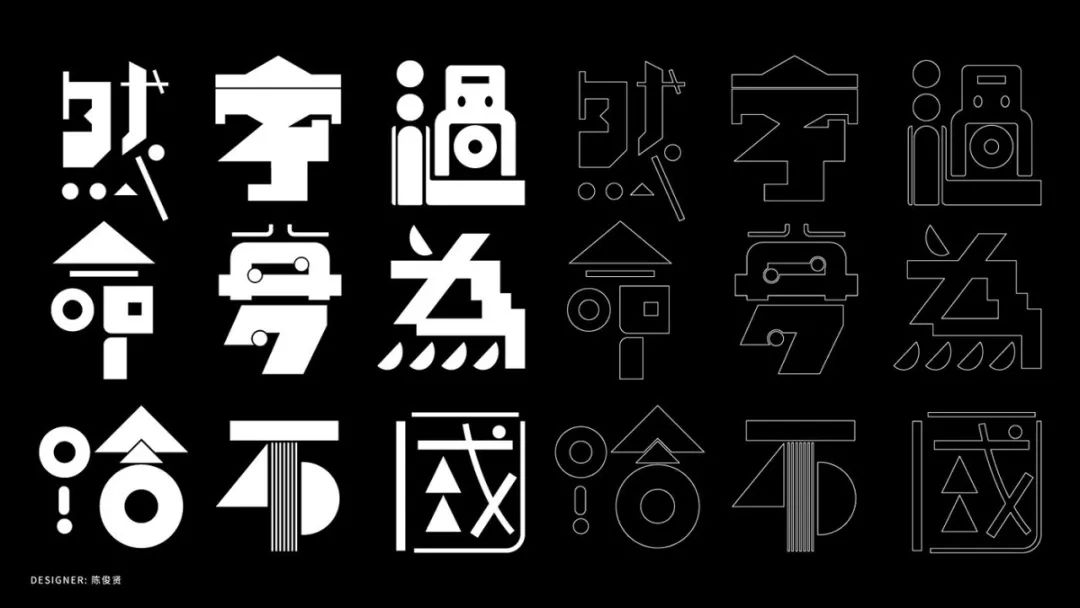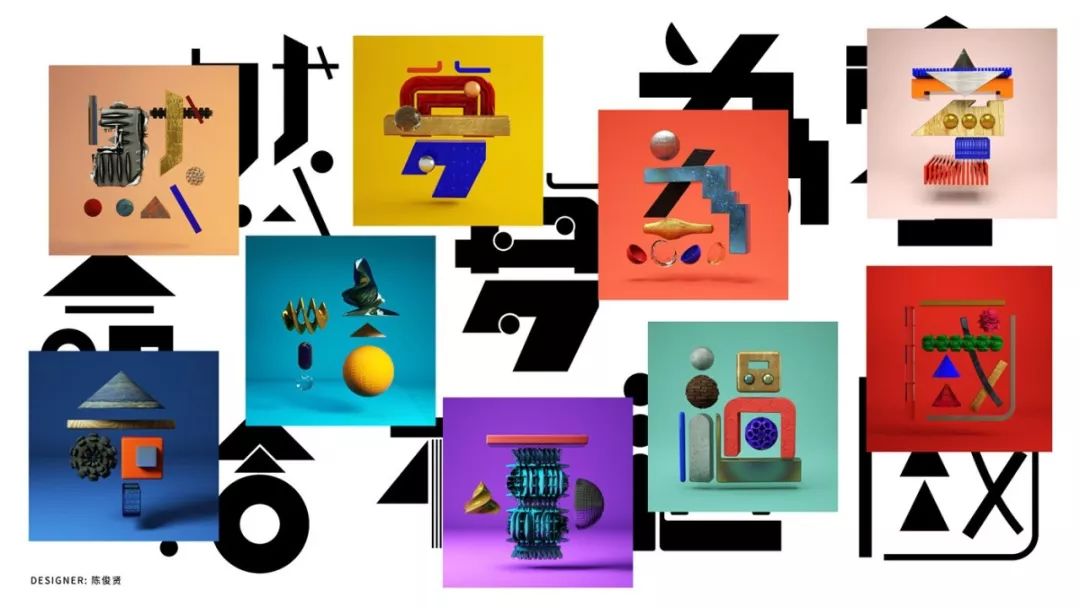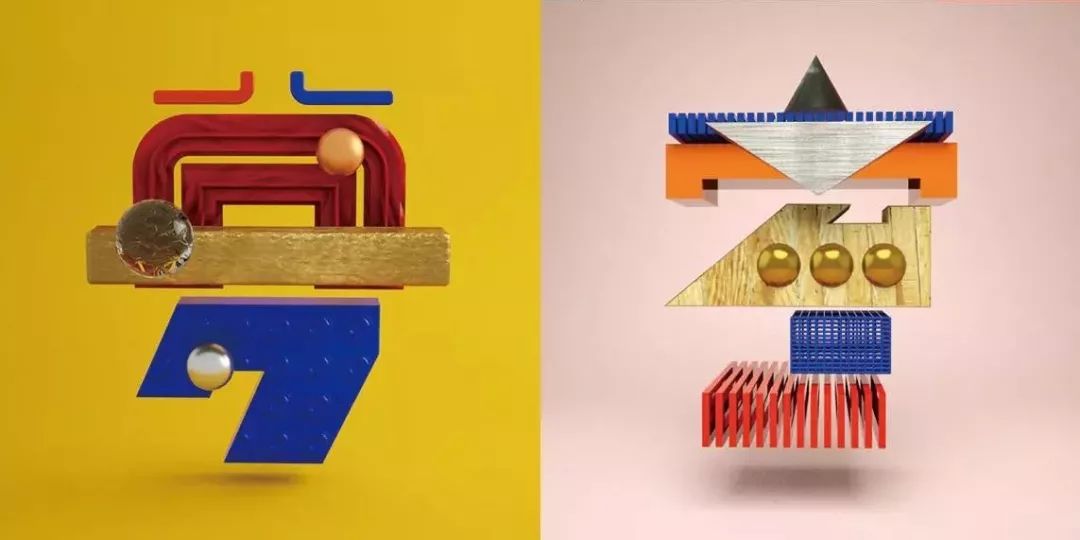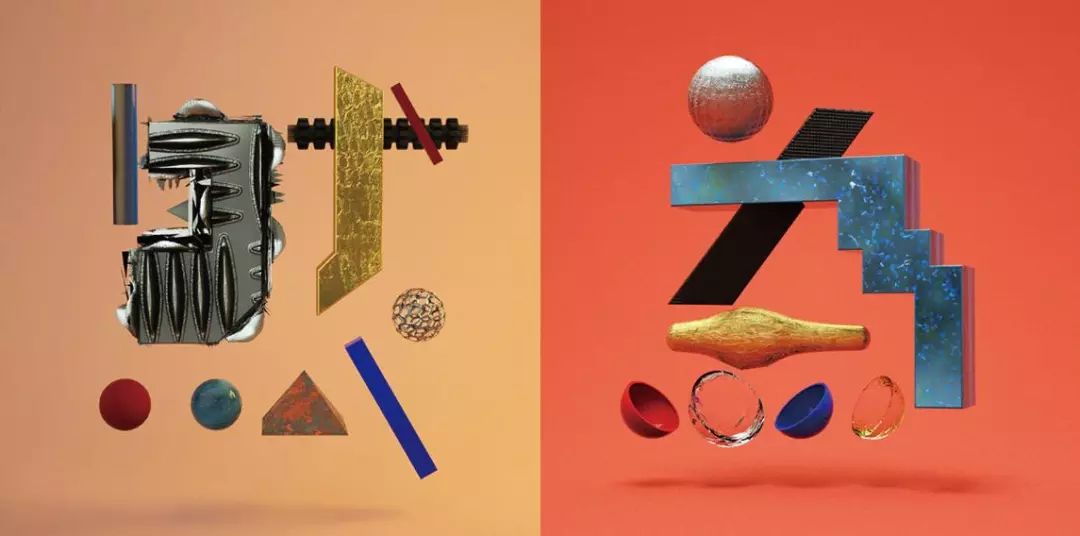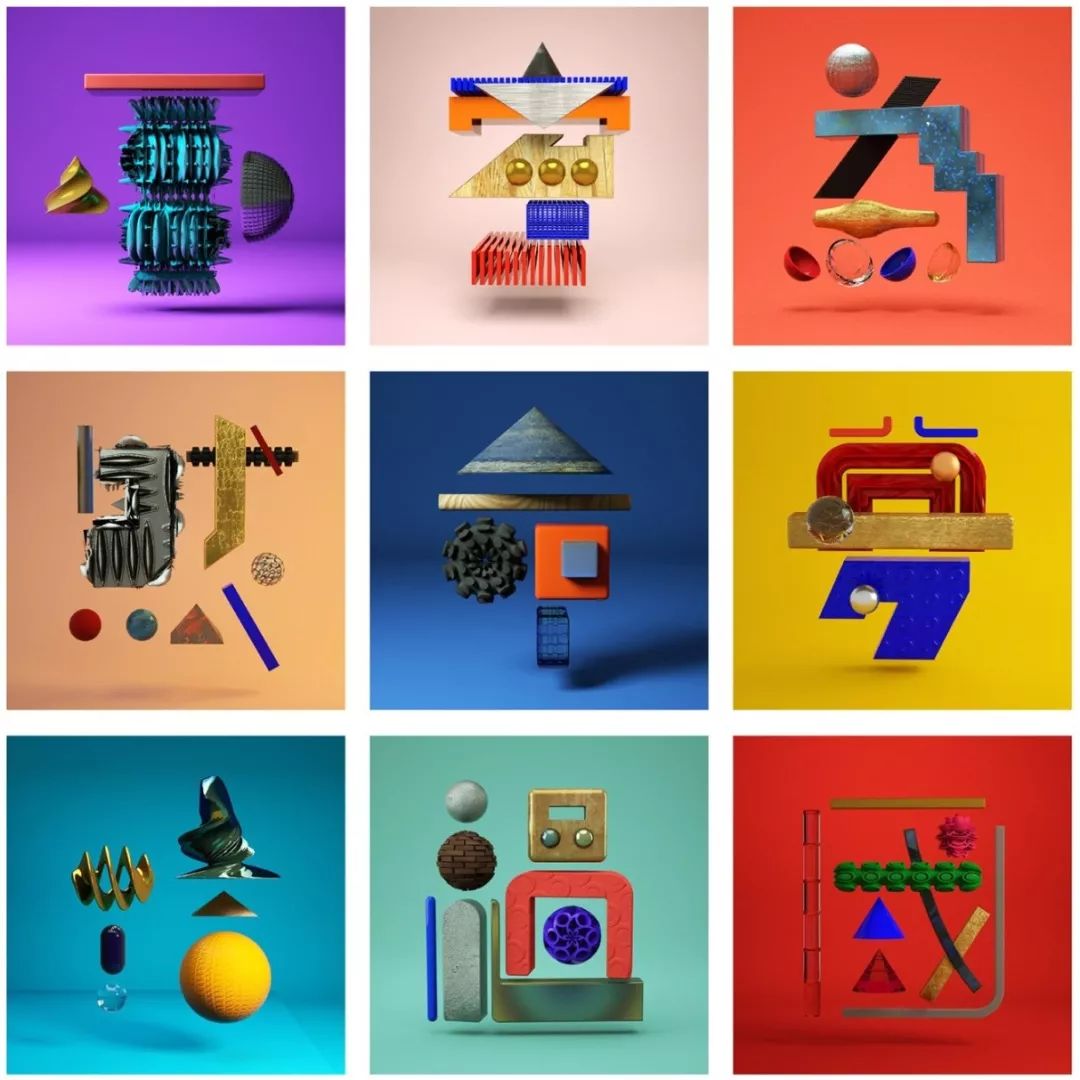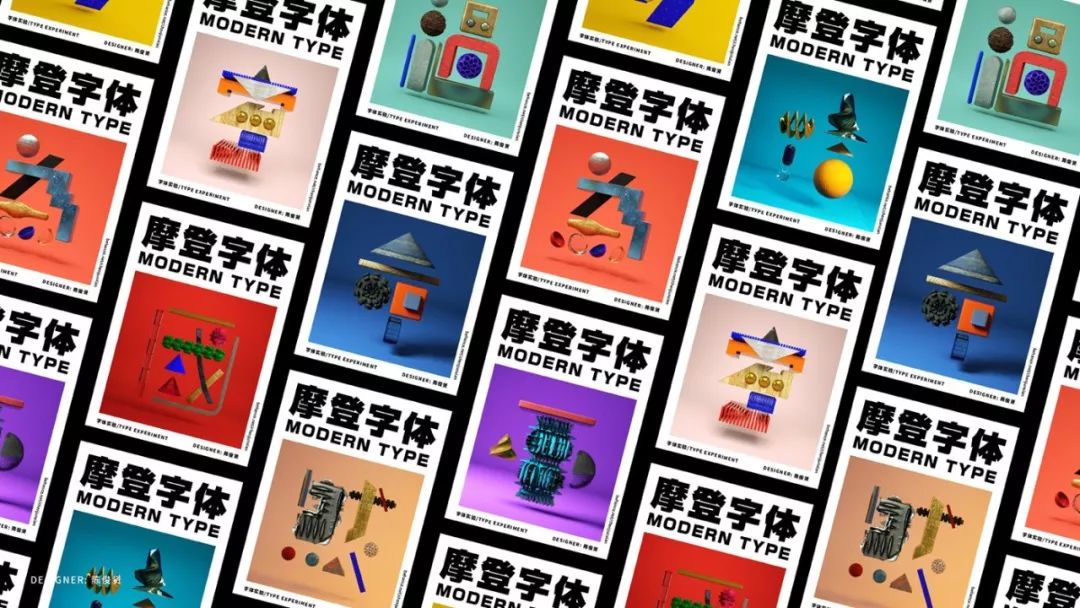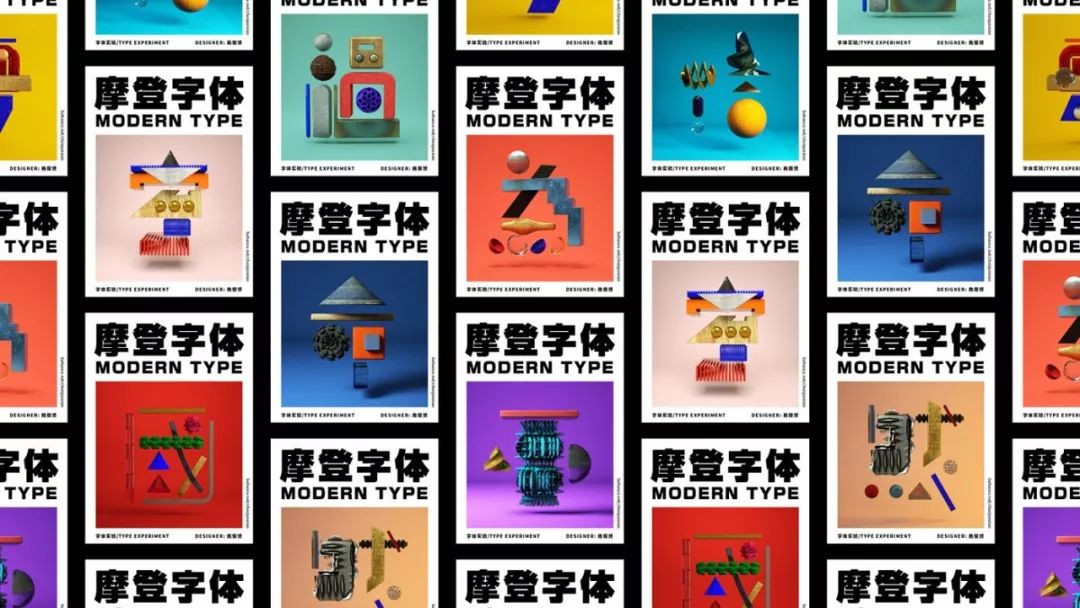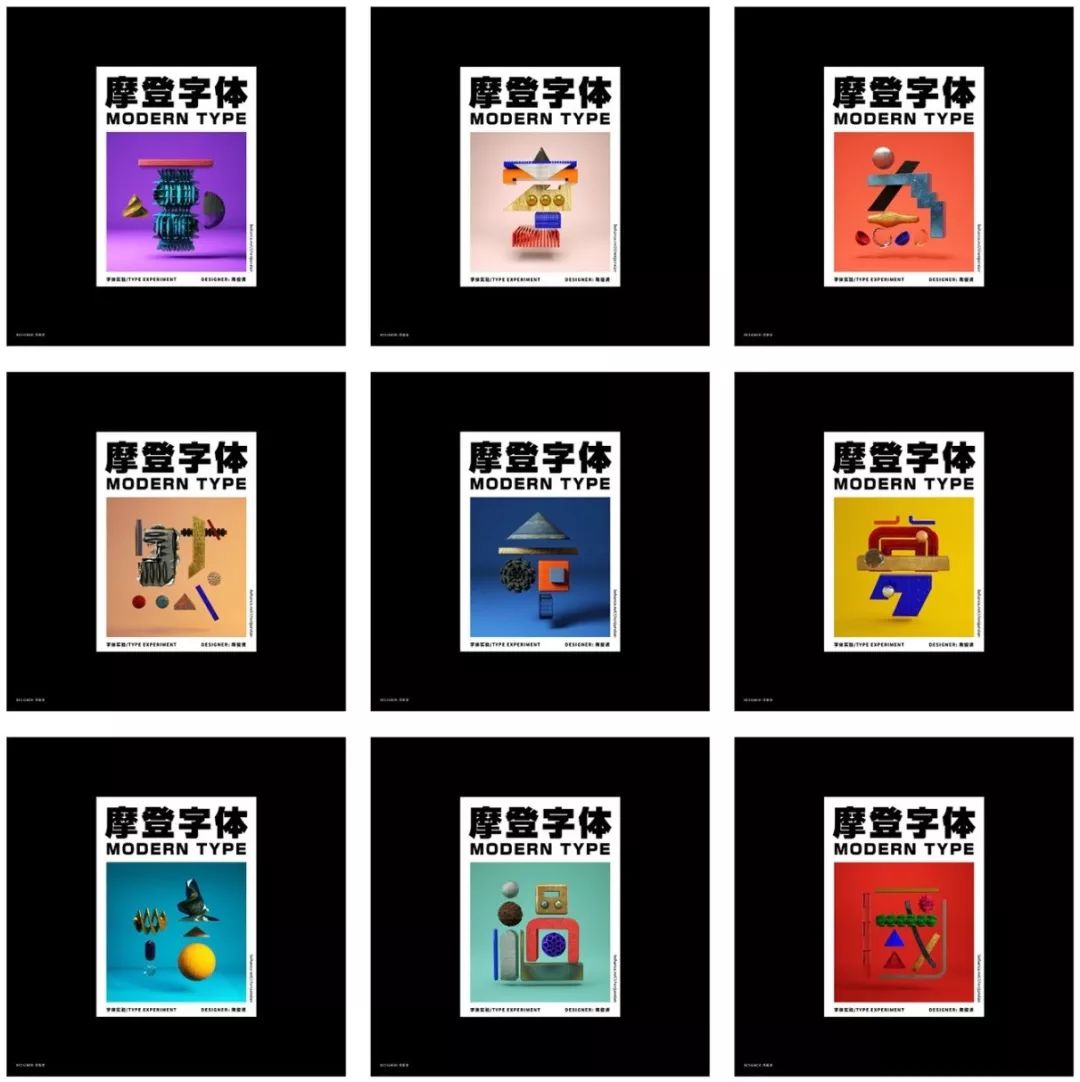
当美术字遇见摩登材质……
今天给大家介绍的这个项目名叫“摩登字体(MODERN TYPE)”,来自广州设计师陈俊贤。
陈俊贤在富有特色的老美术字中,选择了9个繁体中文作为设计素材:過為國字夢不然命給。
老美术字是一种艺术加工的实用字体,因其加工手法而富有装饰意味,从而使汉字在经历悠远的书写长河之后,呈现一种全新的“摩登”面貌。
他选择了一些现代生活中的物件,这些物件造型与字体的笔画相当,AD518猜想他用的应该是C4D软件吧。
当两者结合,产生了一组风格奇特摩登字体,堪称摩登元素与传统汉字的大融合。
整组摩登字体的全貌。